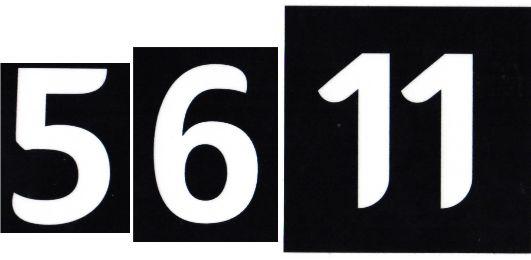
Schriftart mit abgerundeten Kanten für Ziffernaufkleber
weiß jemand um welche Schriftart es sich auf dem Foto handelt?
Ich habe nur diese Zahl als Vorlage und muss aber mehrere Zahlen setzen für Aufkleber.
Leider kann ich diese Schrift bisher nicht identifizieren.
Auf den ersten Bilck geht das für mich in Richtung FF Cocon (Evert Bloemsma für FontFont, 1998). Möglicherweise sind die Ziffern im Nachhinein modifiziert worden – vielleicht ist es aber auch eine Schriftart, deren Gestalter die FF Cocon zum Vorbild genommen hat.